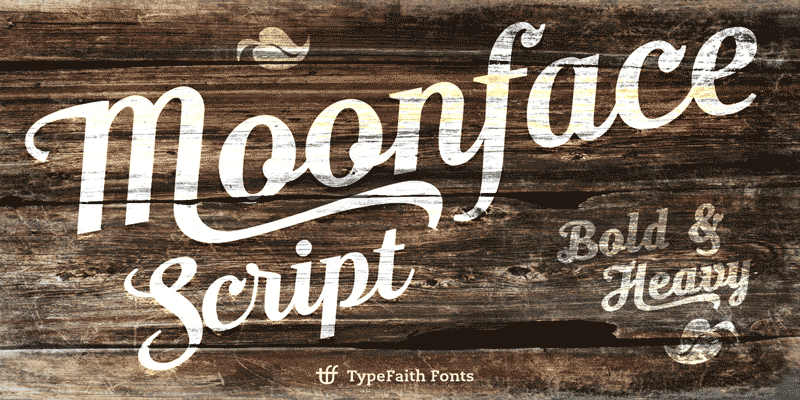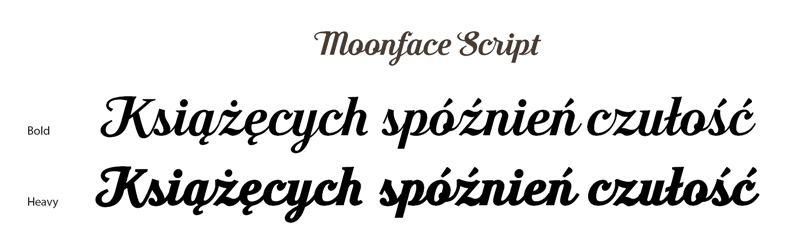
Font Moonface Script
Zakupiliśmy nowy font ozdobny Moonface Script, zaprojektowany w 2013 roku przez Léona Hulsta z Holandii. Ten charakterystyczny ozdobny font zawiera 2 odmiany  grubości i polskie znaki diakrytyczne.
Moonface Script należy do modnej ostatnio grupy fontów retro, o literach ręcznie malowanych pędzlem, szczególnie często wykorzystywanych w tematach związanych z żywnością.